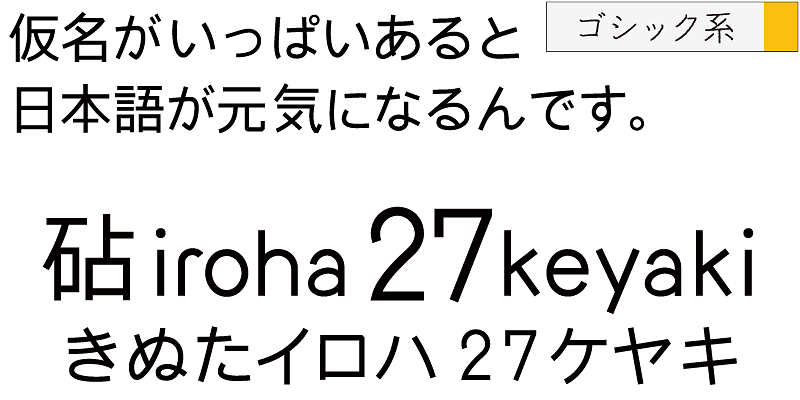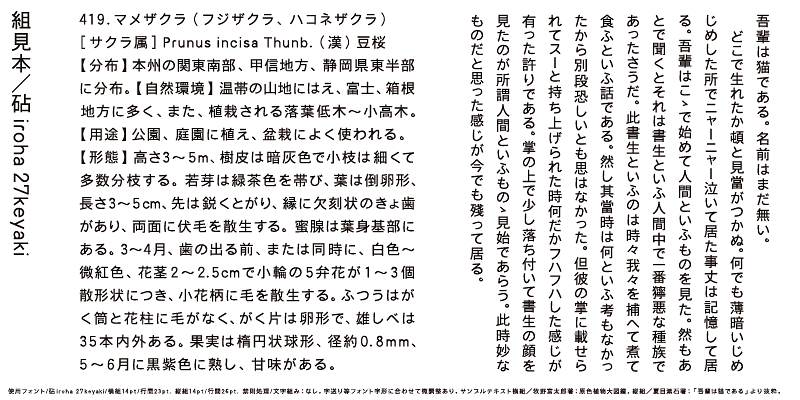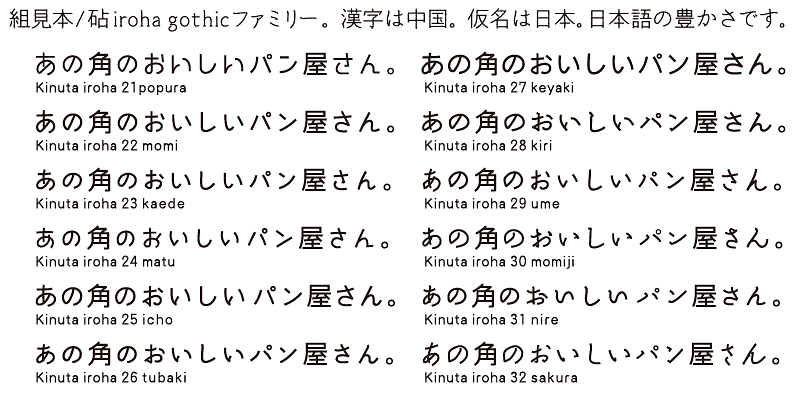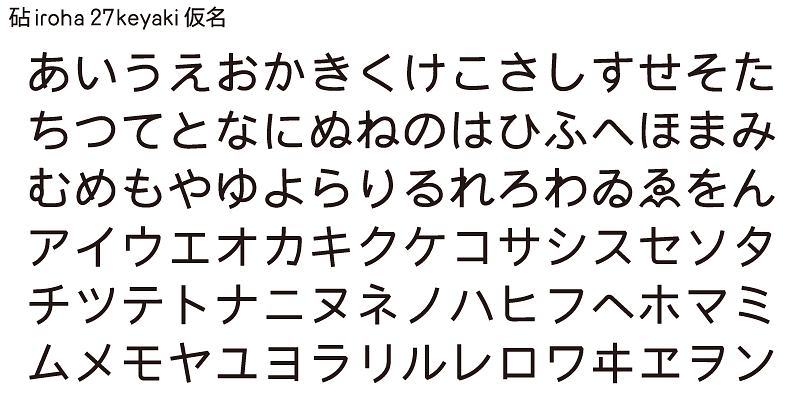
「砧 iroha 27keyaki StdN」は、組んだ時に漢字と同じ大きさに見えることを意識した仮名です。おおらかでゆったりとしています。
iroha の漢字は共通です。直線を意識したシンプルなデザインです。仮名は全部で 12 種類あります。
日本語の特長は、仮名をつかいます。仮名は、中国か らやってきた漢文を日本語読みにするために、日本が 作った文字です。仮名は意味をもつ漢字を主役に言 葉をつないでいきます。それは日本人の優しさや気づ かい、ときにはあいまいさもありますが、どれも小さな 国の人の密度が高い暮らしから生まれた言葉です。 砧(きぬた)書体制作所は、仮名が日本語の原点だ と考えています。その仮名を豊かにすれば、日本語は もっと魅力的になります。日本語の60〜70%は、仮 名です。仮名をかえると文字組の表情もかわります。 仮名はシンプルで動きのある曲線構成、その表現は、 無限の世界です。日本語の豊かさは、仮名に託されて います。砧書体制作所のフォントに仮名のバリエー ションが多いのはそのためです。